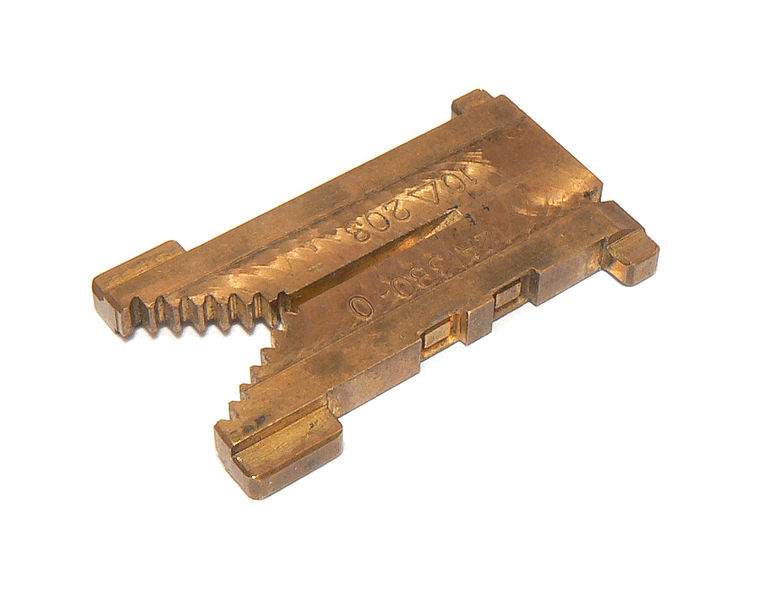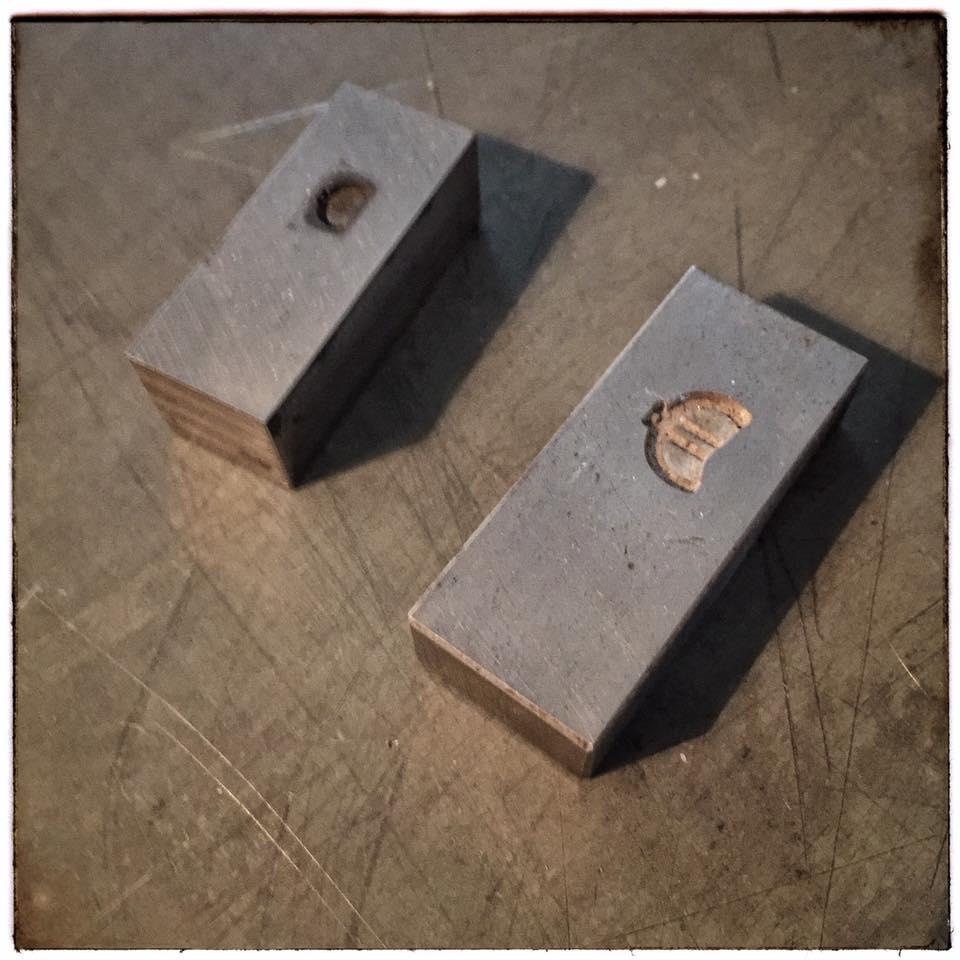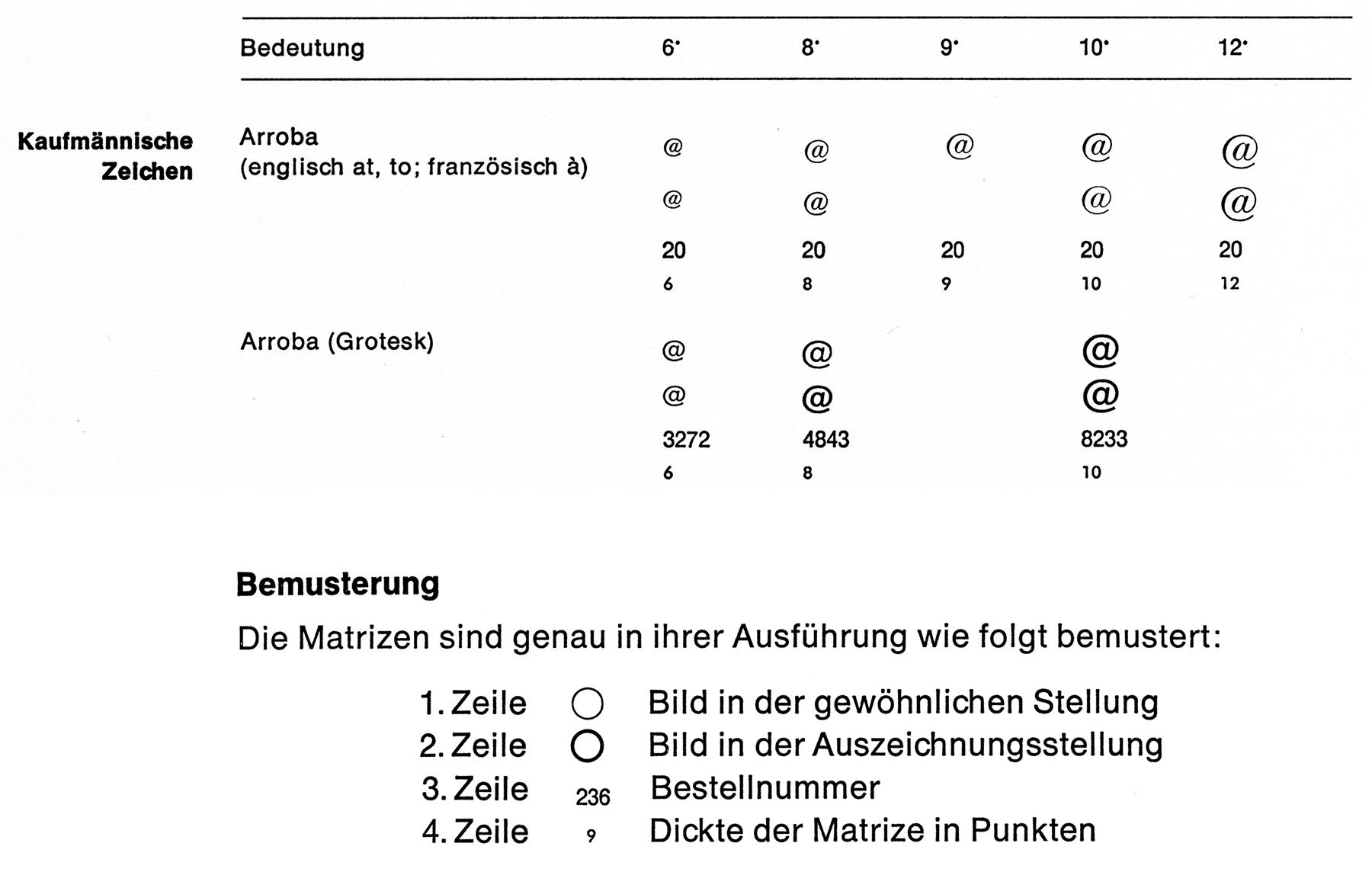
Gibt es irgendwo @-Matrizen in Grotesk und Antiqua?
Was leider aus der Webseite nicht so deutlich hervorgeht: Herr Gerstenberg ist in der Lage fast jemals von der Stempel AG gefertigten Schriften und auch Schmuckverzierungen zu gießen.
Bei meinem letzten Besuch dort fragte ein Kollege aus der Schweiz, ob er ihm die @-Zeichen auch in 8 Punkt größe auf einem 10 Punkt Kegel gießen könne. Da Herr Gerstenberg diese nicht auf Lager hatte, werden sie eigens für den Kunden (nach)gegossen.
Soweit ich es in Erinnerung habe gibt es das @-Zeichen jedoch nur in einer Antiqua-Form, nicht als Grotesk-Form.
Ich wüsste nicht, was da der große Unterschied sein soll … beides sind Formen in die Blei gegossen wird, zum Zwecke eine Hochdruckform daraus zu erhalten.
Nicht ganz...  Eine Linotype-Matritze ist eine (teil)Gußform, in der dann die Linotype-Zeile gegossen wird. In einer Matritze ist die Glyphe als Hohlform enthalten, diese istr so geformt, dass diese automatisch nach dem Abguss wieder in das richtige Fach geleitet werden kann:
Eine Matritze für den klassischen Handsatz ist der Abdruck des geschnittenen Stahlstempels in einem quaderförmiges Stück Kupfer, welche in den Gießapparat eingespannt wird, um darin die Letter zu gießen.:
die Kupferfarbenen Teile sind die Matritzen, daneben silberfarben die damit gegossenen Lettern, die noch nicht zugerichtet sind, also noch den Anguß besitzen:
In so fern dienen die zwar dem gleichen Zweck, aber besitzen eine unterschiedliche Form.
Ich habe beides schon in der Hand gehabt … auch wenn der technische Arbeitsablauf differiert, beides sind Matritzen.
Ich habe sogar die Matrizen für die Eurozeichen von Rainer Gerstenberg fotografieren dürfen, die bietet er auch an.
Wozu braucht man ein Petit-@ auf Korpus-Kegel? Die Zeichen sind auf Gevierte gegossen, die kann man unterlegen, zumal man, sollte die Schriftlinie nicht stimmen, nicht nur unter- sondern auch überlegen muß, was mit dem Zeichen mit angegossenem Durchschuß nicht ginge. Jedenfalls nicht ohne erhebliche Bastelei.
Die Schriftgießerei Wagner hat auch serifenlose @ mit gleichbleibender Strichstärke verkauft. Aber bei deren Auflösung scheinen die Matrizen teilweise verschollen zu sein. Es sind ja auch ganze Schriftsätze von Wagner bis heute nicht mehr aufgetaucht.
Nach @-Matrizen für die Monotype könnte man auch im Hamburger Museum der Arbeit fragen. Also ob sie was doppelt haben. Gießen können sie sie jedenfalls, die Lettern kann man dort bekommen.
... solange der Thema-Ersteller sich in Schweigen hüllt und uns keine weiteren Hinweise gibt was er tatsächlich sucht, werden alle Überlegungen ins Leere führen.
Es handelt sich bei den gesuchten Matrizen tatsächlich um Maschinenmatrizen für unsere wieder in Funktion genommene Intertype C4 mit Jahrgang cirka 1960 ... notabene aus einem 25 Jahre dauernden Dornröschenschlaf.
Für Einzeltypen wende ich mich selbstverständlich an die Giesserei von Herrn Gerstenberg.
Guten Tag, ja solche.
Gibt es diese evtl. ab Lager?
Sind die Intertype-Matritzen kompatibel mit denen der Linotype?
Wenn ja, evt. mal bei Fritz von Rechtern in Neukirchen-Vlyun anfragen. Der verkauft gerade alles, was nicht niet- und nagelfest ist und hatte auch einen großen Bestand an Linotype-Matritzen, nebst einer noch funktionierenden Linotype!
Liebe Bleisatzfreunde
grundsätzlich sind die Linotype- und die Intertype Matrizen, wie sagt man so schön , kompatibel.
Es gilt nur zu beachten, dass es sich dabei um Handmatrizen (für die Setzmaschine) handelt. Das heisst die Matrizen werden nach dem Giessvorgang wieder über den separaten Kanal an der Seite der Maschine ausgeschieden. In einen Kanal im Magazin wäre das sonst eine eher ungünstige Angelegenheit ...